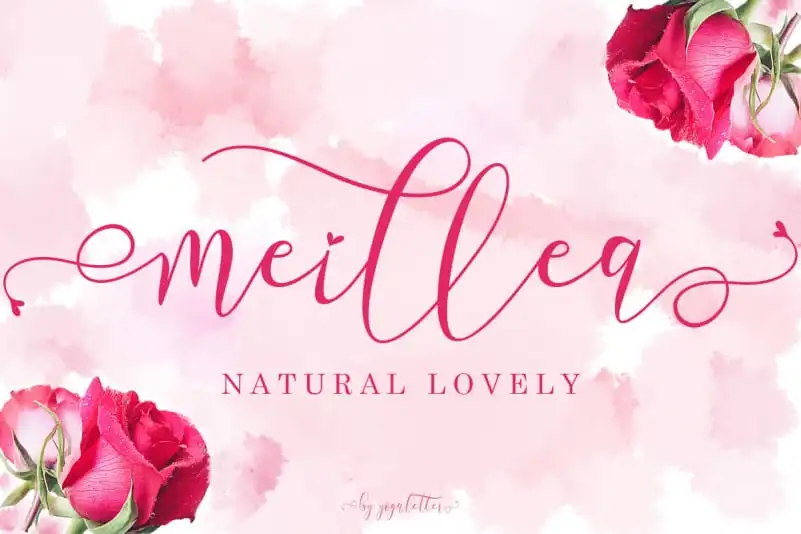
Meillea Calligraphy Font
A Meillea Calligraphy Font é uma fonte alta qualidade que foi criada com um toque delicado, resultando num belo e elegante traço perfeito para vários tipos de trabalho. Esta fonte é ideal para todos os requisitos de noivado (invites de casamento, fotografia de casamento, decorações e outras designs do casamento). Ela também é perfeita para promover o seu negócio – hotéis, vilas, lugares de férias, produtos ou serviços de promoção. Além disso, ela se adapta perfeitamente a atualizações de promoção, logotipos, marcações, panfletos e atualizações de status nas redes sociais. O designer Yoga Letter trouxe uma delicada graça à Meillea Calligraphy Font, criando um traço único que combina elegância com suavidade. Seja para aplicar em cartões de convite, ou na arte da decoração do casamento, sua perfeita fluidicidade e curvatura proporcionam um toque refinado aos seus designs. É uma escolha inteligente para quem busca expressar a delicadeza de suas mensagens com estilo, seja através das letras de cartões de convite ou dos logos que representam seu negócio. Neste design, o designer Yoga Letter capturou perfeitamente as nuances da calligrafia elegante tradicional, resultando em uma fonte versátil e sofisticada. Seja para um projeto pessoal de escrita ou para a criação de materiais profissionais, Meillea Calligraphy Font é uma excelente opção para quem deseja dar vida aos seus projetos com uma graça única e sofisticada.